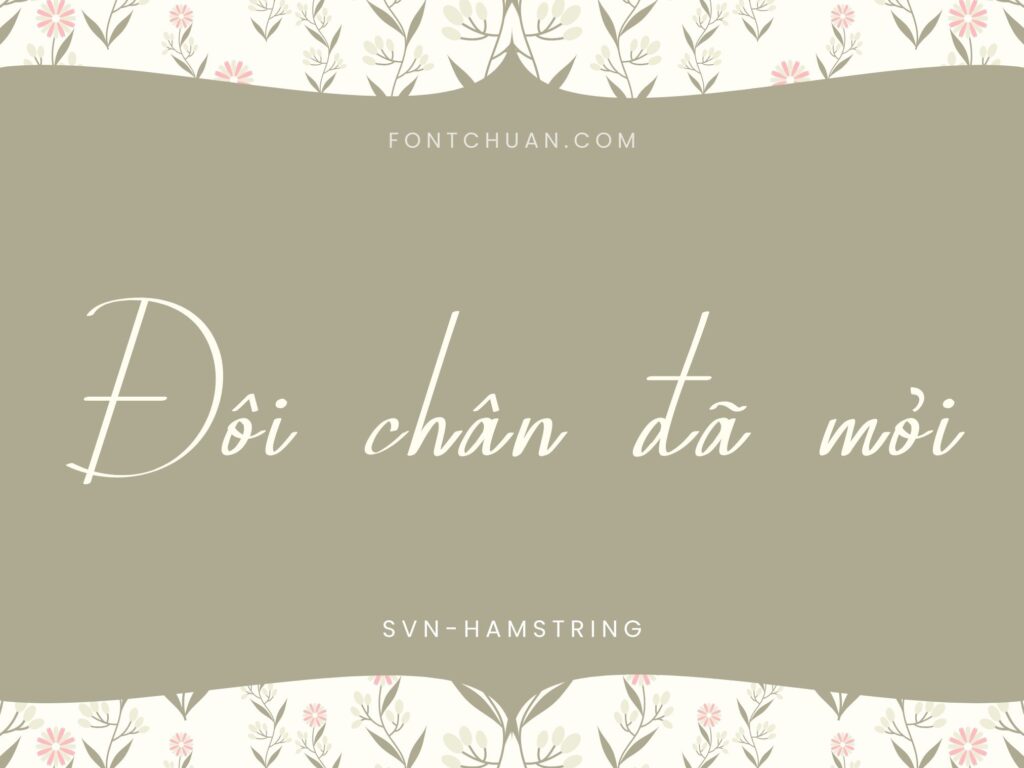
Font SVN Hamstring Việt Hóa
Tác giả Font: Widiyanti & Sarah Suci P
Font SVN Hamstring là phiên bản Việt hóa của kiểu chữ Hamstring, được thực hiện bởi Styleno.1 Fonts. Hamstring là một kiểu chữ viết tay mang phong cách chữ ký cổ điển, được thiết kế bởi Widiyanti & Sarah Suci P và phát hành bởi RaisProject. Font này nổi bật với các chữ cái hoa mỹ và đường nét mềm mại, tạo cảm giác thanh lịch và tự nhiên. Hamstring bao gồm đầy đủ chữ hoa, chữ thường, chữ số và các ký tự đặc biệt, phù hợp cho nhiều mục đích thiết kế khác nhau.
SVN Hamstring lý tưởng cho các dự án thiết kế yêu cầu sự cá nhân hóa và tinh tế, như thiệp mời, logo, tiêu đề và các ấn phẩm truyền thông. Các ngành nghề như thiệp cưới, ẩm thực và spa có thể tận dụng font này để tạo điểm nhấn trong thiết kế. Ngoài ra, font cũng thích hợp cho các sự kiện như Tết, Valentine, Sinh nhật và các lễ hội khác.